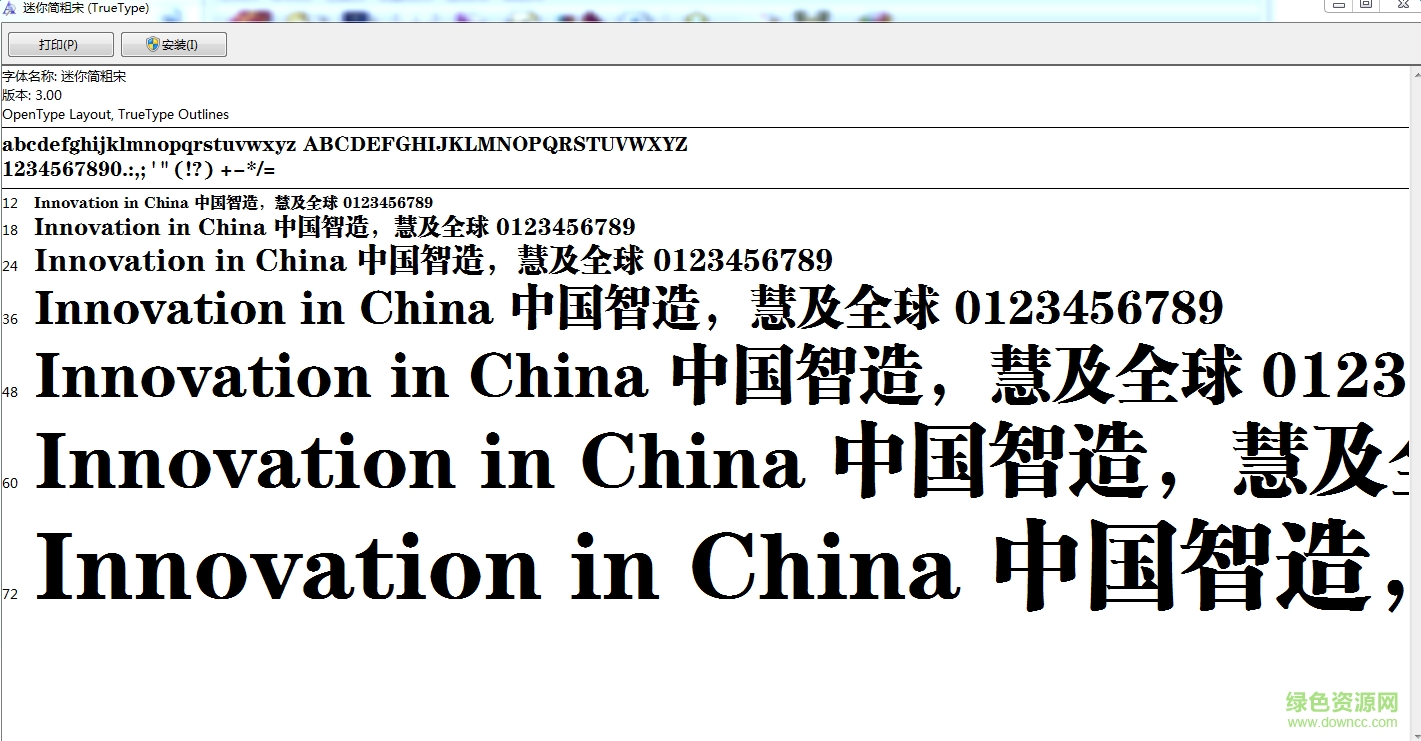
jcusong是什么字體?jcusong字體是一款迷你粗宋字體,比起一般的宋體要粗很多,可以用作注釋說明,正文排版、ppt設(shè)計(jì)、平面設(shè)計(jì)中,需要的朋友趕緊下載吧!
現(xiàn)代鉛字主要采用宋體印刷。后來依據(jù)西方文字的黑體和意大利體的方式,在漢字印刷體中也創(chuàng)造了黑體的鉛字。目前宋體、黑體、仿宋體和楷體成為漢字印刷的主要四種字體。
字重大壁畫粗的字,自然會(huì)給人一種有力,厚重的感覺。
字重小筆畫細(xì)的字,會(huì)給人一種纖細(xì),秀氣的感覺。